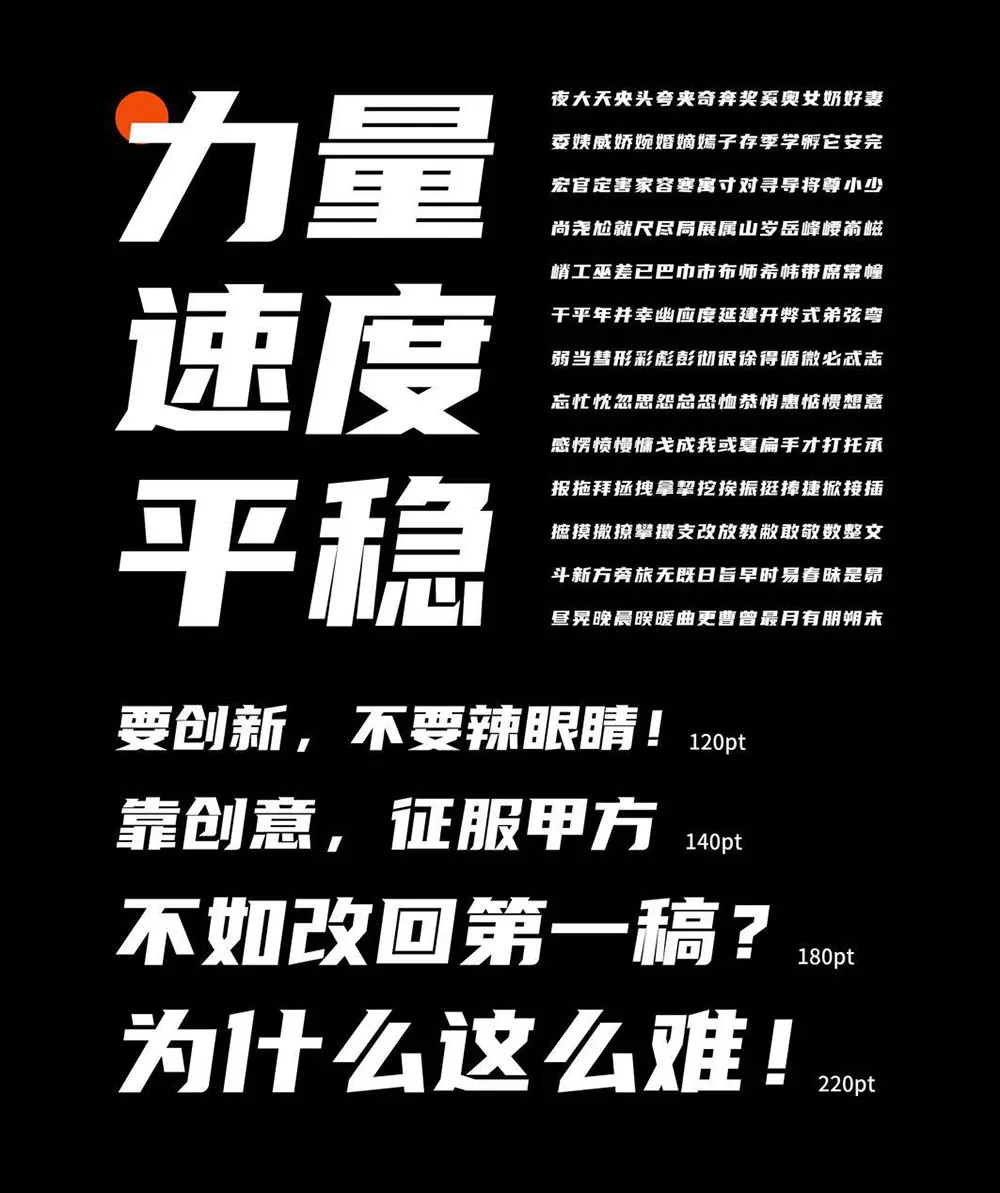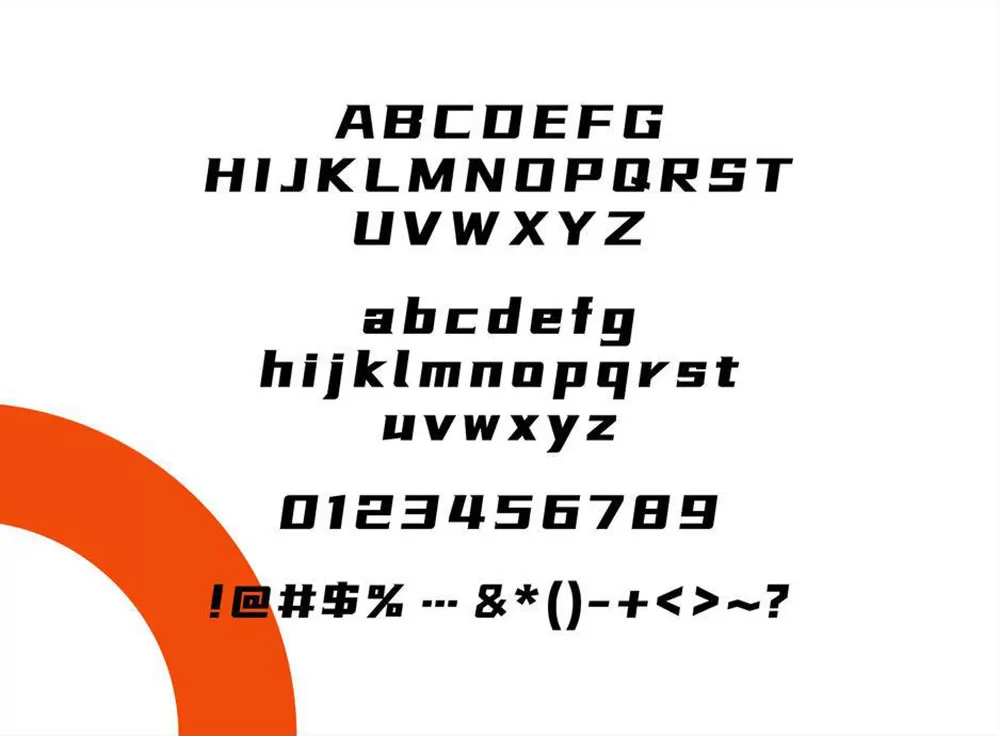
优设标题黑
优设标题黑是一款适配场景广泛,兼具强劲速度感与视觉力量感的专业美术标题字体。
它以黑体字为设计基底,字形整体沉稳大气,同时凭借加宽的字面尺寸与厚重的笔画线条,进一步强化了字体的力量质感。所有字符均采用 8° 水平倾斜的设计巧思,赋予字体十足的动感与速度张力;为了让倾斜形态依旧保持视觉上的稳固性,设计师特意将字身打造为宽扁比例。而在起笔和弯钩位置融入的尖角设计更是独具匠心,不仅凸显出鲜明的几何美学风格,还能为后期的二次调整提供便利。
由此可见,这款字体用于各类品牌广告与产品包装的标题创作,无疑是绝佳之选。